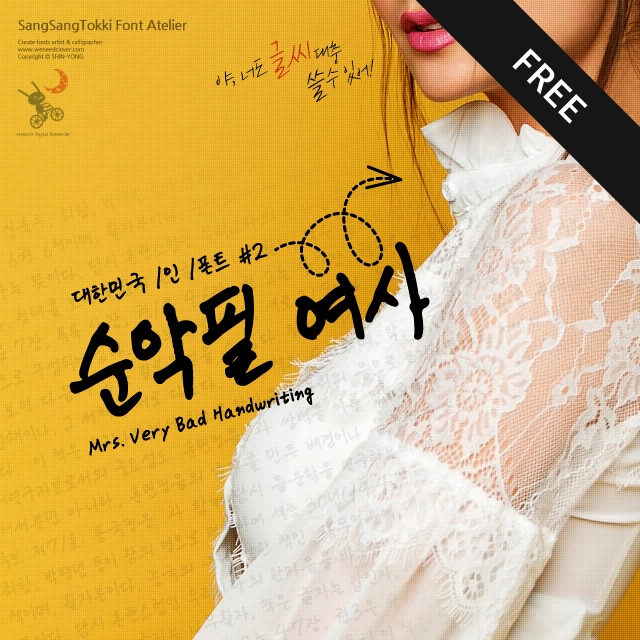
순악필 여사
대한민국 대표 워킹맘 권여사가 공개하는 지렁이 담넘어가는 솔직한 손글씨, 순악필 여사!
학창 시절엔 공부하느라, 취업 해서는 일하느라, 결혼 해서는 육아하느라 글씨 이쁘게 쓸 시간이 없었던 대한민국 대표 워킹맘 권여사가 공개하는 지렁이 담넘어가는 솔직한 손글씨 <순악필여사>는 상상토끼 용이 작가의 대한민국 1인1폰트 두번째 주인공인 권여사님의 손글씨를 기초로 해서 만들어진 폰트입니다. 소중한 글씨로 멋진 폰트를 만들게 허락해준 권여사님께 감사의 마음을 전합니다. |